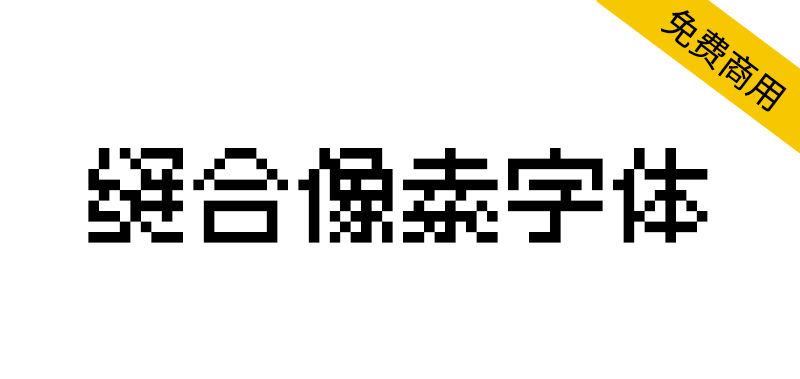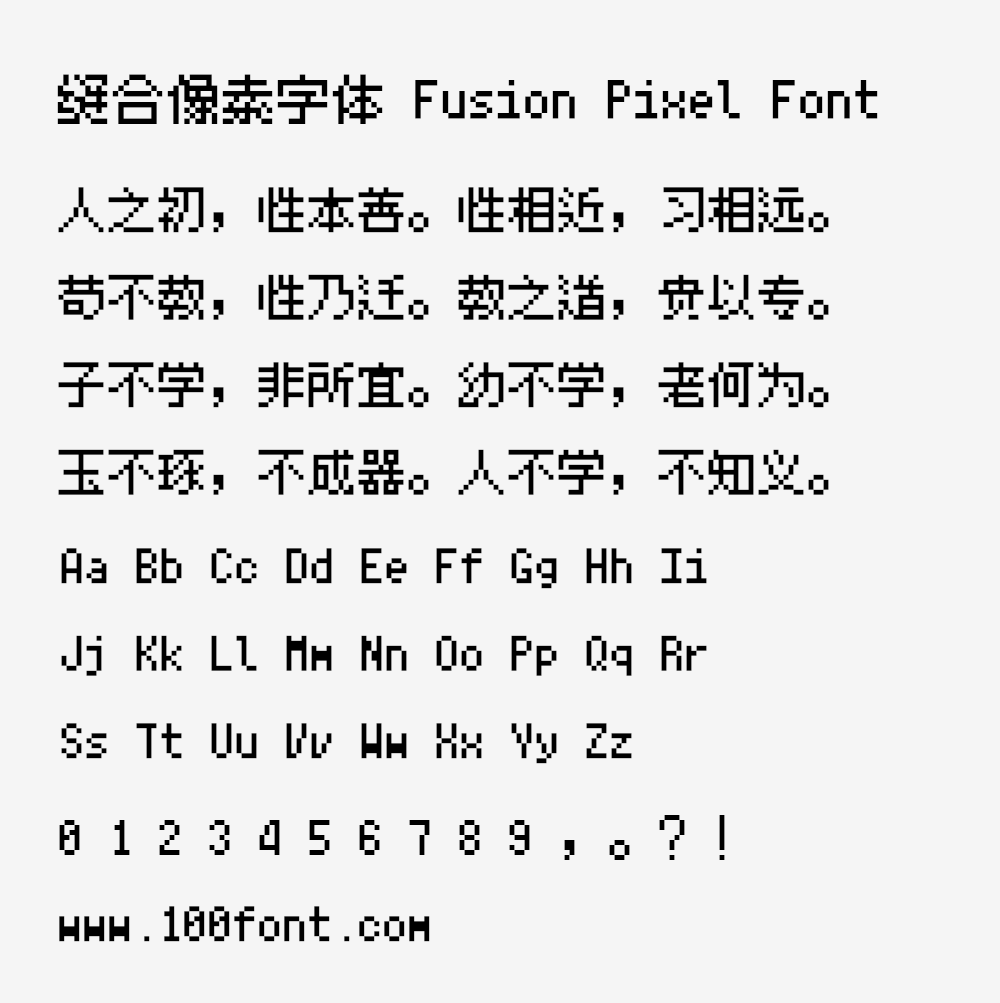
【缝合像素字体】开源的泛中日韩黑体无衬线像素字体
缝合像素字体(Fusion Pixel Font)是一款开源的泛中日韩像素字体,黑体无衬线风格,支持8、10 和12 像素。该项目为「方舟像素字体」的临时性过渡方案,使用多个像素字体合并而成,因此以「缝合」命名。目前支持的语言有 “ 中文-简体、中文-繁体、日语、朝鲜语、拉丁语 ”,尽管如此,这个项目仍然是一个基于补丁的字体解决方案,你不应该对语言特定字形抱有特别的期待。